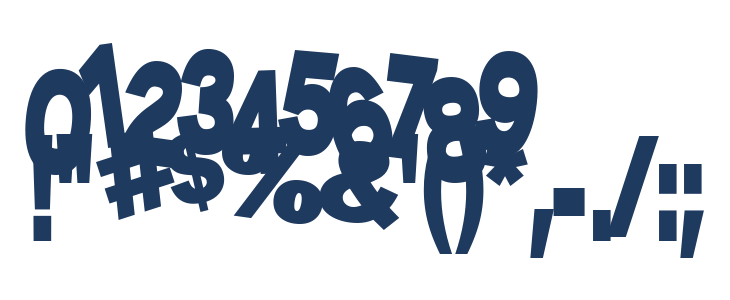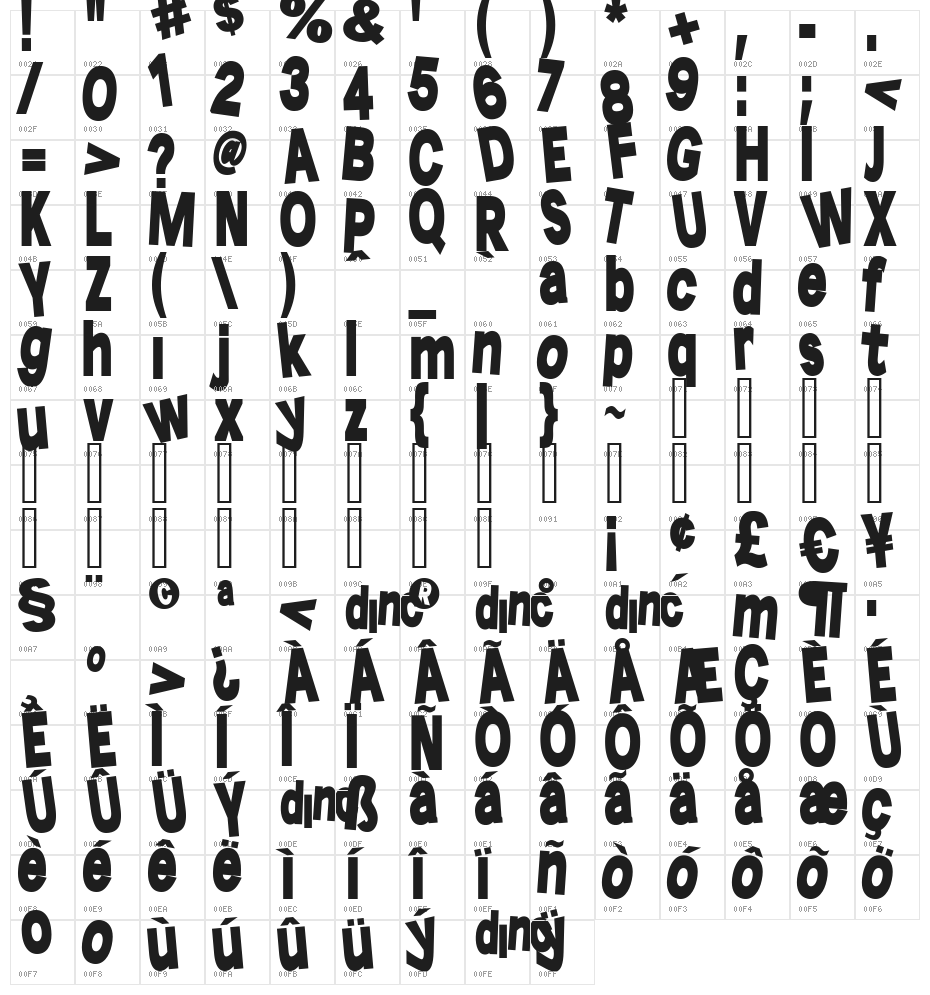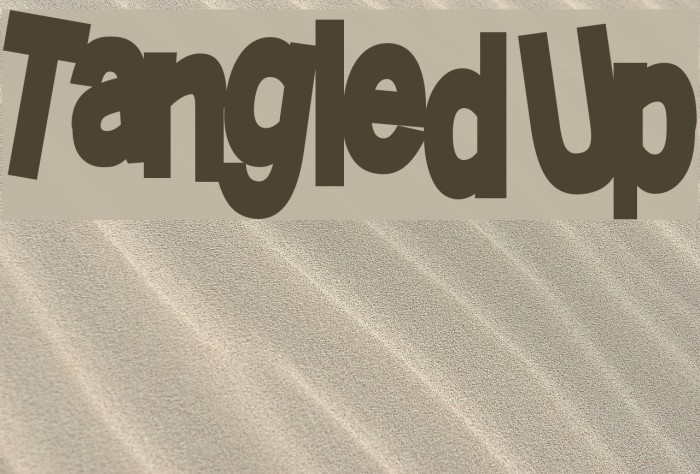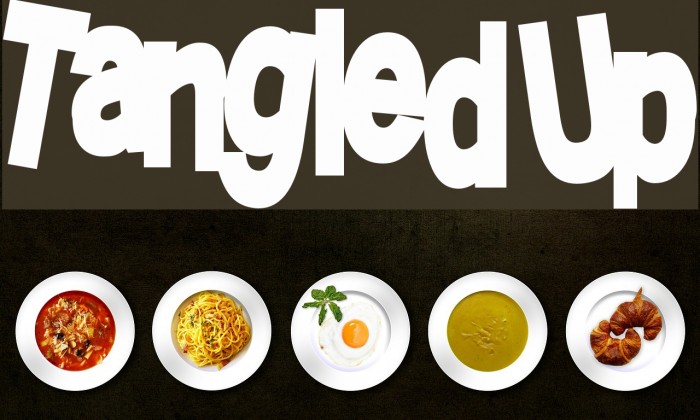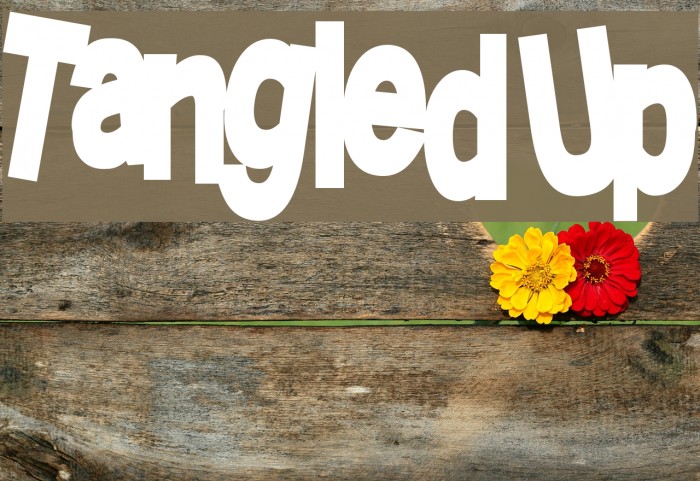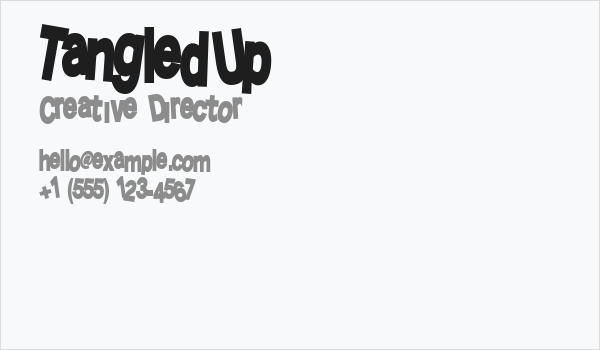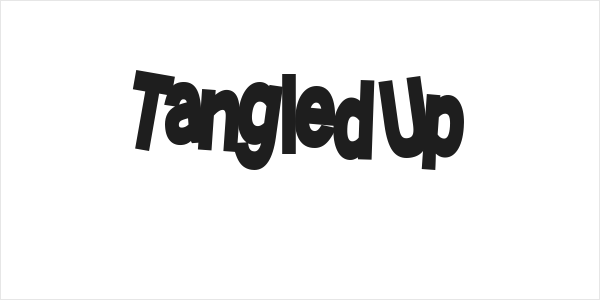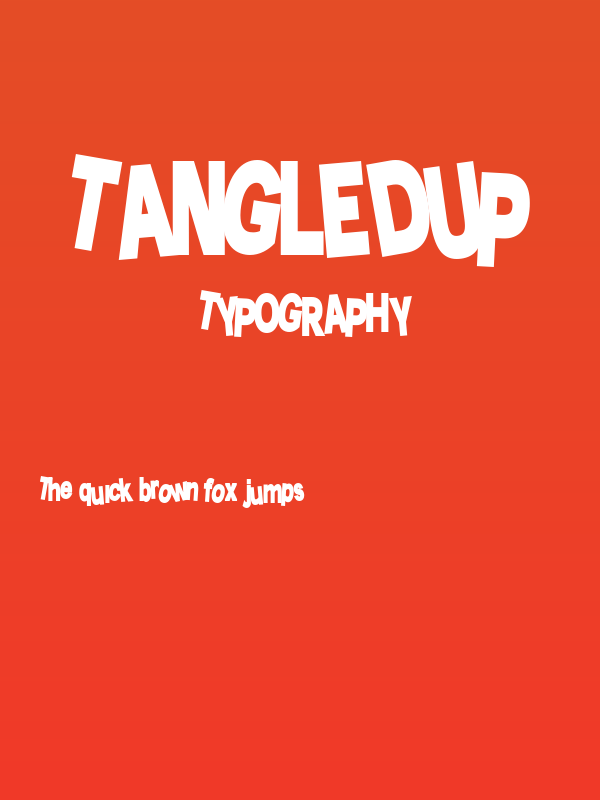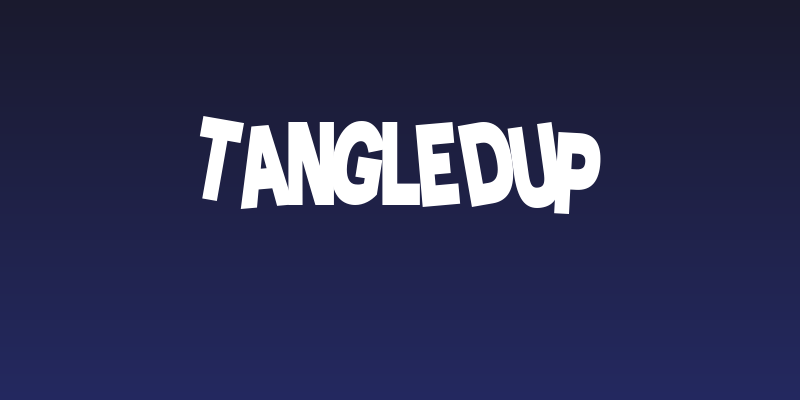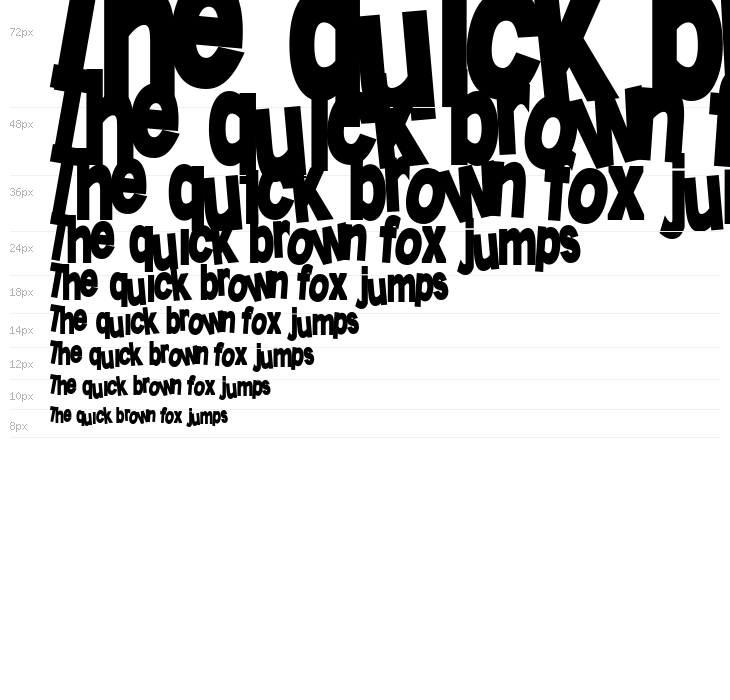
TangledUp Font
TANGLEDUP Groß
TANGLEDUP Kleinbuchstaben
TANGLEDUP Anderer Schreiben
| Gesamtstil | Playful, Whimsical |
| Vorgeschlagene Projekte | Ideal for children's books, playful branding, posters, and creative advertising campaigns. |